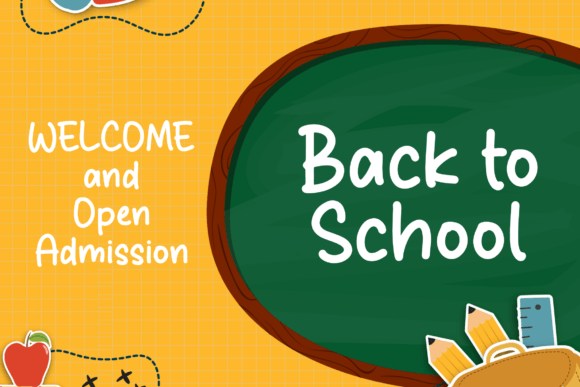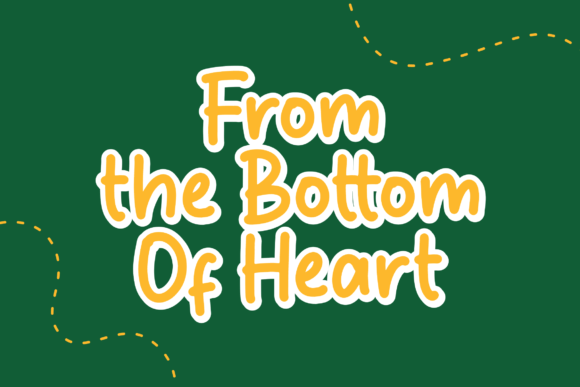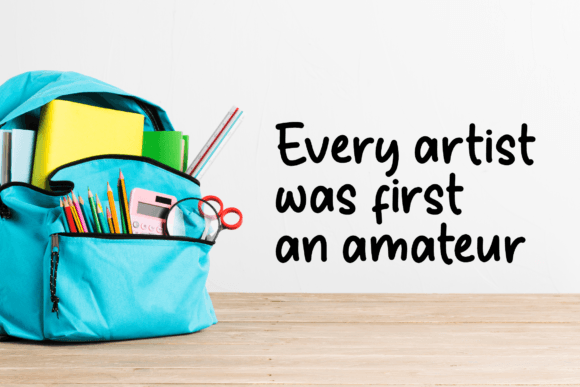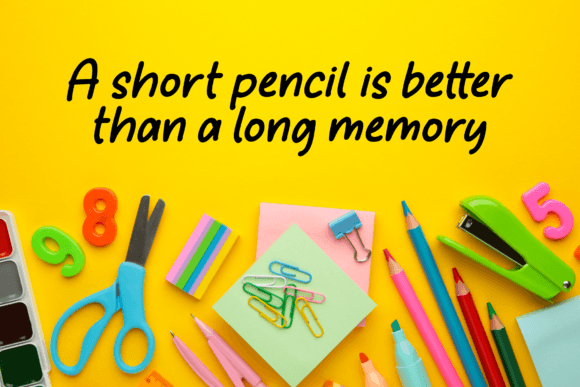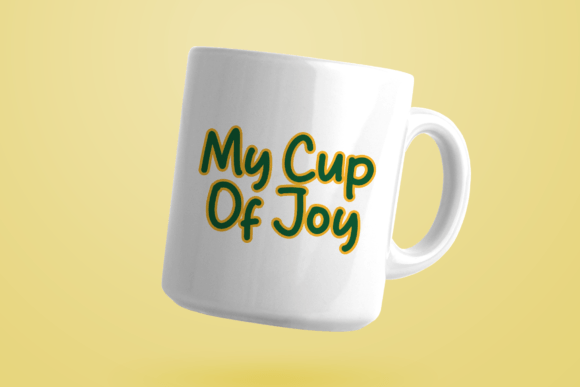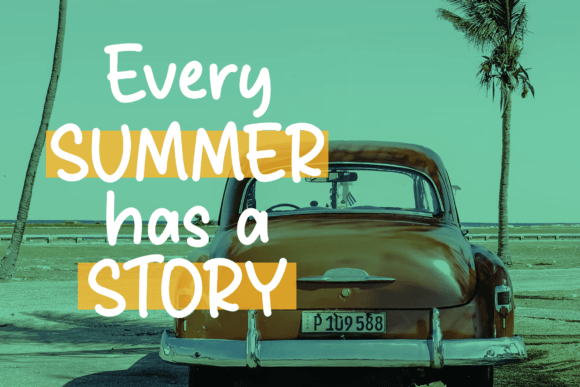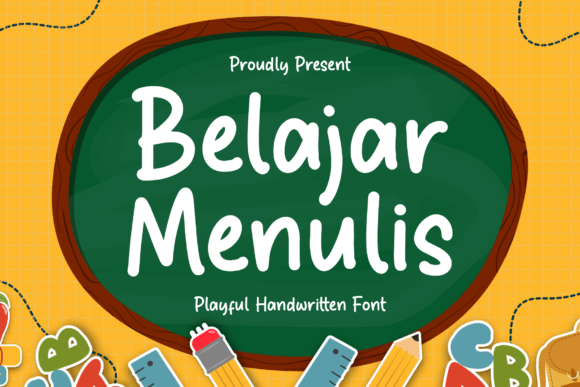
Menemukan Inspirasi Menulis
Siapa di antara Anda yang pernah merasa terinspirasi saat melihat tulisan tangan yang cantik dan unik? Mungkin Anda melihatnya di sebuah buku kuno, atau melihat seorang teman menulis sesuatu dengan tinta yang berwarna-warni. Inspirasi seperti itu bisa membuat kita ingin memiliki penulisan yang sama, dan itu sebenarnya bukanlah hal yang mustahil.
Belajar Menulis Font, font yang kaya akan karakter dan keunikan, hadir untuk membantu Anda menciptakan penulisan yang unik dan menarik. Dengan kemampuan untuk digunakan dalam berbagai proyek, mulai dari logo hingga kartu undangan, Belajar Menulis Font adalah pilihan yang tepat untuk para desainer yang ingin menambahkan sentuhan personal ke dalam karyanya.
Dengan Belajar Menulis Font, Anda bisa menciptakan karya yang lebih menarik dan unik, sehingga Anda bisa membedakan diri dari orang lain. Ini adalah kesempatan untuk mengekspresikan diri dan menciptakan sesuatu yang indah dan berkesan.
Key Features of “Belajar Menulis Font”
- Font Style: A modern, elegant font designed specifically for learning and writing in Indonesian, with unique characteristics that make it easy to read and write.
- Language Support: Designed to support the Indonesian language, with full support for Latin and extended characters, making it ideal for writing and learning in Indonesian.
- Unique Characteristics: Features a unique blend of traditional and modern elements, making it an attractive choice for those who want a font that is both elegant and distinctive.
Designer Review: Belajar Menulis Font
Overall, I think Belajar Menulis Font is a great resource for those looking to improve their handwriting skills. Here are some of the things that work well: ✨
- Engaging content: The lessons are fun and interactive, making it easy to stay motivated.
- Good variety of exercises: The font covers a range of styles and techniques, ensuring that you’ll never get bored.
- Helpful tips and tricks: The instructors offer valuable advice on how to improve your handwriting.
- Limited customization options: The font doesn’t allow for much personalization, which might be a drawback for some users.
- No advanced features: The font is geared towards beginners and intermediate learners, so if you’re looking for more complex tools, you might be disappointed.
Overall, I’d say Belajar Menulis Font is a solid choice for anyone looking to improve their handwriting skills. While it may not be perfect, it’s a great starting point, and the engaging content and helpful tips make it a worthwhile investment.
Belajar Menulis Font: A Practical Application Guide
Tips dan Trik
Untuk mendapatkan hasil yang optimal, pastikan Anda memilih font yang sesuai dengan tema dan tujuan Anda. Anda juga dapat mencoba menggunakan font yang berbeda untuk menambahkan kesan yang unik. Selain itu, jangan lupa untuk mengatur ukuran dan warna font agar mudah dibaca.
Penggunaan Umum
Belajar menulis font sangat berguna dalam berbagai bidang, seperti desain grafis, penulisan artikel, dan pembuatan presentasi. Anda dapat menggunakan font untuk menambahkan kesan yang profesional dan menarik dalam pekerjaan Anda.
Alternatives to Belajar Menulis Font for Designers
Belajar Menulis Font is a tool for creating custom fonts, but it may not be the best fit for every designer. Here are some alternatives to consider:
1. FontForge
FontForge is a free and open-source font editor that allows designers to create, edit, and manipulate fonts. It’s a more advanced tool than Belajar Menulis Font and offers more features, such as support for multiple master fonts and glyph editing. Use FontForge when you need more control over your font’s design and want to create complex fonts.